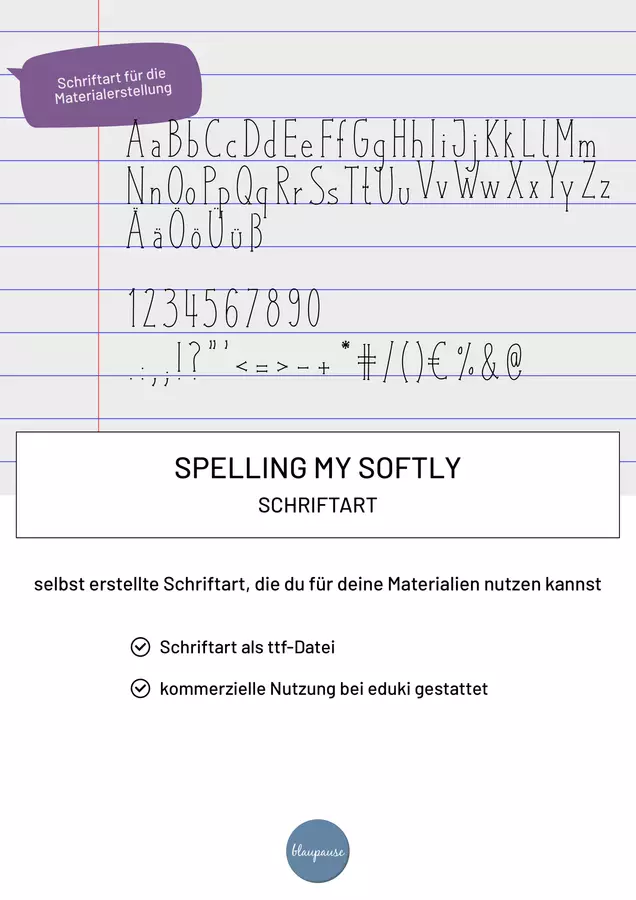
Inspiriert von anderen kreativen lmp-AutorInnen, habe ich ebenfalls eine eigene Schriftart erstellt. Spelling Me Softly ist eine sehr feine und schmale Serifenschriftart. Enthalten sind alle Groß- und Kleinbuchstaben, Ziffern und (die wichtigsten) Sonderzeichen.
Spelling Me Softly - Schriftart